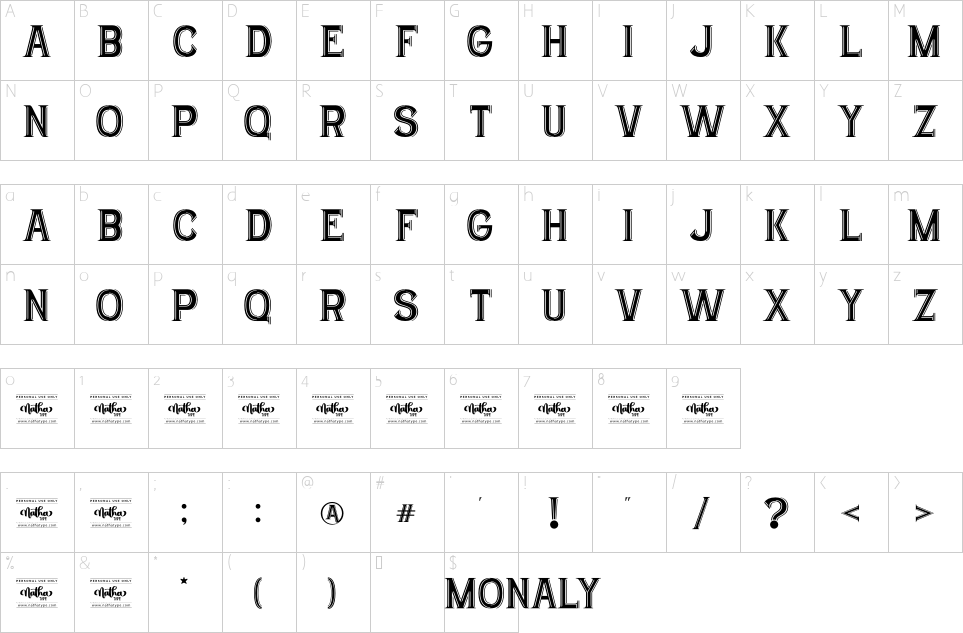
Aqui está uma descrição em português do Brasil, envolvente e natural, para a página de download da fonte Monaly: Monaly é uma fonte de estilização gráfica e artística, desenvolvida pelo Natha Type. Ela foi projetada para criar um visual atraente e único em qualquer aplicativo de texto. Possui uma variedade de traços e opacidades, permitindo que você customize o estilo da sua mensagem de diversas maneiras. Monaly é um presente para os designers e criadores de conteúdo, oferecendo flexibilidade para expressar ideias de maneira criativa. Com 879 downloads até o momento, ela é uma fonte elegante e versátil que vai enriquecer seu trabalho gráfico. Não hesite em experimentá-la para ver como ela pode se adaptar a diferentes projetos.